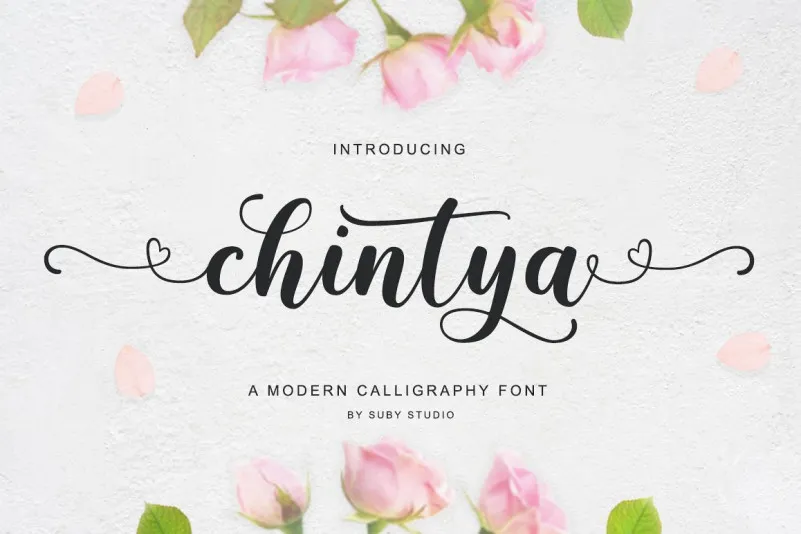
Chintya Script Font – Download Grátis
A fonte Chintya Script é uma nova criação do designer Suby Studio que traz alegria aos seus escritos. Esta fonte chamada Chintya vem com um toque fresco e genuinamente feito à mão, transformando palavras em sentimentos delicados e adoráveis. Ideal para logos, identidades de marca, convites, cartões de presente, designs de casamento, postagens nas redes sociais e muito mais, Chintya Script oferece um toque elegante e moderno. Em um mundo cheio de estímulos visuais, a Chintya é perfeita para quem deseja algo único que traga uma sensação única aos seus projetos. Uma combinação de elegância e modernidade, esta fonte vem com todas as características necessárias para complementar qualquer tipo de projeto visual, garantindo tanto qualidade quanto originalidade. Não há dúvida de que Chintya Script é uma escolha brilhante para aqueles buscando adicionar um toque especial aos seus projetos digitais ou impressos.